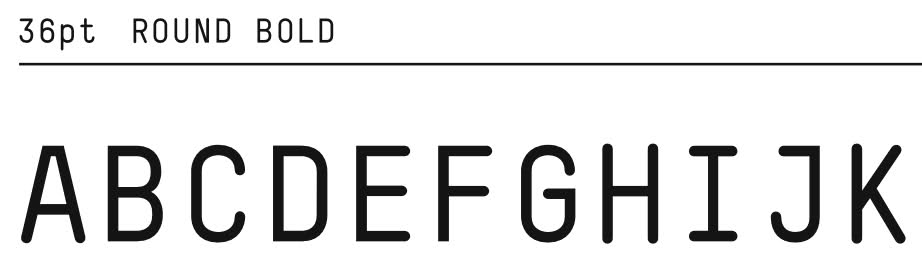
Suche diese moderne Schrift
Ich bin auf der Suche nach dieser Schrift, konnte sie aber bisher nicht entdecken und gebe die Suche bei diversen Schriftanbietern vorerst auf. Vielleicht kann mir jemand von euch weiter helfen?
Alles, was ich gefunden habe, war viel eckiger...
Danke, Robert für deinen Vorschlag! Das sind ganz neue Typo-Welten, die sich da auftun. Hab jedenfalls von der Schrift vorher noch nie was gehört.
Sie gefällt mir super gut, nur mit dem großen A werde ich noch nicht ganz warm, das ist sehr flach oben:
T-Star Mono Round
...dafür ist das G in deinem Beispiel runder, als bei mir. Ich möchte sie für die Typo unter einem Logo nehmen, Text komplett in Großbuchstaben und die Typo beginnt blöderweise mit "A".
Das Muster ist (glaube ich) fotografiert aus einer Zeitschrift. Hab mal eine Zeit lang schöne Typo archiviert, aber zum Teil leider nicht mit Herkunft und oft nur Fragmente.
Ich HOFFE, es ist eine echte Schrift, nicht gebastelt, die man auch kaufen kann!?
Gravurschrift!!! Das ist ein gutes Stichwort!